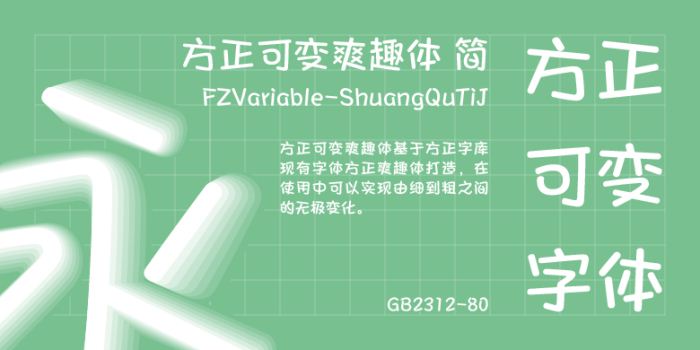
方正可變爽趣體由方正字庫(kù)郭炳權(quán)設(shè)計(jì)師出品的藝術(shù)字體,實(shí)現(xiàn)字形的平滑連續(xù)的細(xì)微調(diào)整,爽趣體利用跳躍不規(guī)則的筆畫(huà)組合而成,充分顯示如兒童般的天真可愛(ài),適合應(yīng)用于藝術(shù)設(shè)計(jì)、平面宣傳設(shè)計(jì)、網(wǎng)頁(yè)設(shè)計(jì),書(shū)法等領(lǐng)域。
方正可變爽趣體 支持文字粗細(xì)無(wú)級(jí)調(diào)節(jié),設(shè)計(jì)師通過(guò)調(diào)整字重軸(Weight)的變化,可以實(shí)現(xiàn)字形的平滑連續(xù)的細(xì)微調(diào)整,滿足不同版式的設(shè)計(jì)需求。
爽趣體利用跳躍不規(guī)則的筆畫(huà)組合而成,充分顯示如兒童般的天真可愛(ài),無(wú)拘無(wú)束,自由自在,活力十足。爽趣體包含各種不同粗細(xì),適合各種快消食品、玩具產(chǎn)品以及圖書(shū)漫畫(huà)等的宣傳廣告和包裝設(shè)計(jì)。。